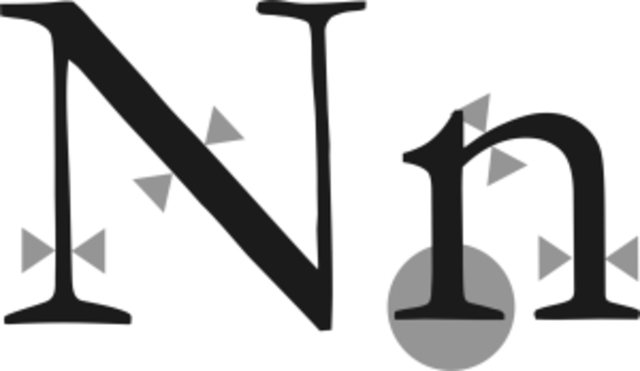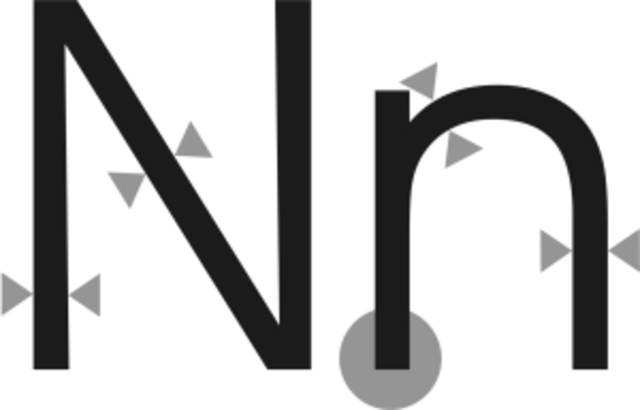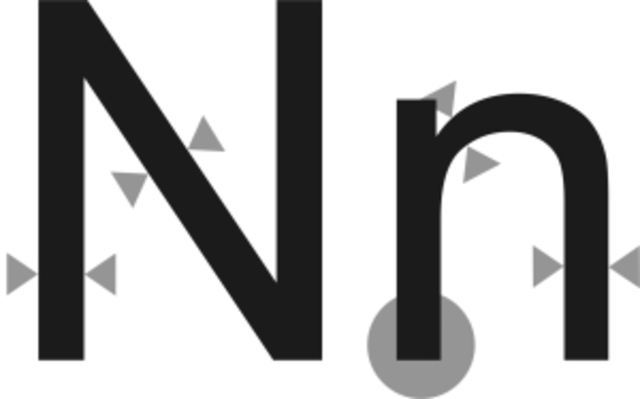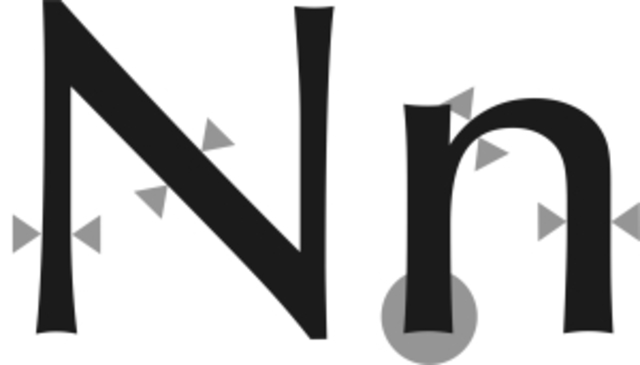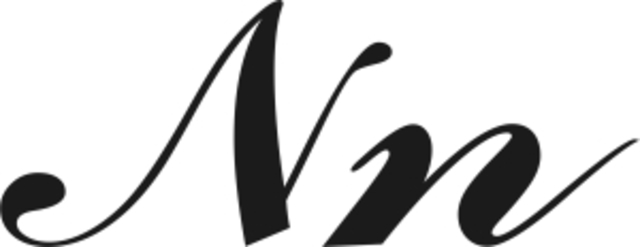
Las Romanas Antiguas, son tipografías que poseen serif triangular y presentan diferencias en los trazos. Derivan de las inscripciones romanas, originalmente talladas en piedra. En general son tipografías con buena legibilidad y se utilizan habitualmente para textos de largo alcance. (Ejemplos: Garamond / Times / Bembo)
Garamond (diseño original de Claude Garamond. 1550) -
Las tipografías Romanas Modernas, presentan serif lineal o filiforme y una gran diferencia entre los trazos gruesos y finos. Al igual que las romanas antiguas, derivan de los textos esculpidos en piedra, en las construcciones y monumentos romanos. (Ejemplos: Bodoni / Modern / Didot)
Bodoni (diseño original de Giambattista Bodoni. 1784) -
Las tipografías Egipcias se distinguen principalmente por el serif cuadrangular. Pueden presentar o no diferencia en los trazos. En general son más pesadas que las romanas, y son utilizadas frecuentemente para títulos o rótulos. No es aconsejable su uso para textos largos. (Ejemplos: Clarendon / Serifa / Schadow)
Clarendon (diseño de Robert Thorme y Benjamin Fox. 1845) -
Las tipografías góticas, al igual que las otras tipografías del grupo cursivas o script, se inspiran en la escritura manual, aunque además de presentar normas y reglas muy precisas en su construcción, exhiben una morfología característica, propia del estilo, producto del elemento escriptor utilizado en la escritura original y su particular forma de uso. (Ejemplos: Cloister Black / Goudy Text / Fette Fraktur)
Cloister Black (diseño de Morris Fuller Benton. 1904) -
Las tipografías de estilo caligráfico, al igual que las tipografías gestuales imitan o se inspiran en la escritura hecha a mano, aunque en este caso su ejecución ostenta una serie de normas estrictas en cuanto a alineaciones e inclinaciones, al igual que una marcada utilización de la pluma recortada como elemento escriptor. (Ejemplos: Commercial Script / Shelley / Bickham)
Commercial Script (diseño de Morris Fuller Benton. 1908) -
Las tipografías de estilo Humanista, al igual que las geométricas y neo-grotescas, no presentan serif. Exhiben modulaciones en sus trazos, aunque puede o no existir diferencia entre ellos. Se distinguen por un aspecto suficientemente orgánico como para ser consideradas como las de mejor rendimiento de lectura, entre las tipografías sin serif. (Ejemplos: Optima / Gill Sans / Britannic)
Optima (diseño de Hermann Zapf. 1952) -
Las tipografías gestuales expresan la fuerza y la gracia del trazo hecho a mano. Las fuentes de este estilo, que aparecen en los sistemas informáticos, “imitan” la escritura a mano puesto que, sin dudas se basan en la escritura manuscrita, pero han sufrido una serie de correcciones y ajustes en el transcurso del proceso de digitalización. (Ejemplos: Mistral / Brush / Choc)
Mistral (diseño de Roger Excoffon. 1953) -
Del grupo de las tipografías sin serif, son en general unas de las más utilizadas para textos de corto y mediano alcance. Las tipografías Neo-grotescas presentan muy buena legibilidad en palabras o frases cortas, por lo que son consideradas como las más apropiadas para ser empleadas en señalizaciones. (Ejemplos: Helvetica / Frutiger / Univers)
Helvetica (diseño de Max Miedinger. 1957) -
Las tipografías de paloseco geométricas no presentan ningún tipo de serif o remate ni diferencia en los trazos. Se caracterizan por una construcción rígida, donde predominan las formas geométricas en apariencia puras. Las rectas pronunciadas y las formas circulares hacen que no sea una tipografía aconsejable para la utilización en bloques de texto. (Ejemplos: Avant Garde / Futura / Kabel)
Avant Garde (diseño de Herb Lubalin. 1970)